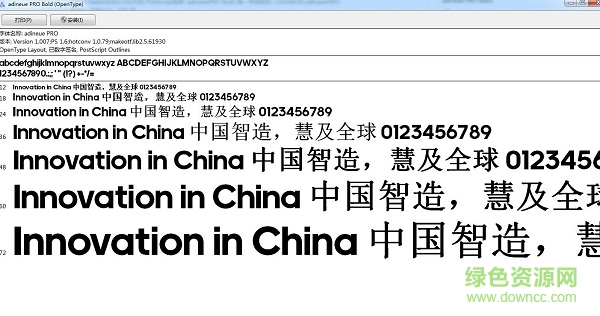
adineuepro字體
adineue字體包包含了adineue pro bold字體和adineue bold等字體,該字體整體結(jié)構(gòu)看起來非常平整,粗細(xì)線條對(duì)比不明顯,閱讀體驗(yàn)不錯(cuò),有需要者歡迎免費(fèi)下載!
無襯線體的分辨特征
Neo-Grotesque: 簡(jiǎn)單形態(tài)的g, 筆劃均勻,x-height較高;
Geometric: 能看出圓形和方形的組合,a和g是簡(jiǎn)單形態(tài)的;
adineuepro字體
Humanist: 手寫體的影響,筆劃粗細(xì)變化向手寫靠攏;
Grotesque: 風(fēng)格比較模糊,筆劃不均但不模仿手寫,G的豎是突出的。